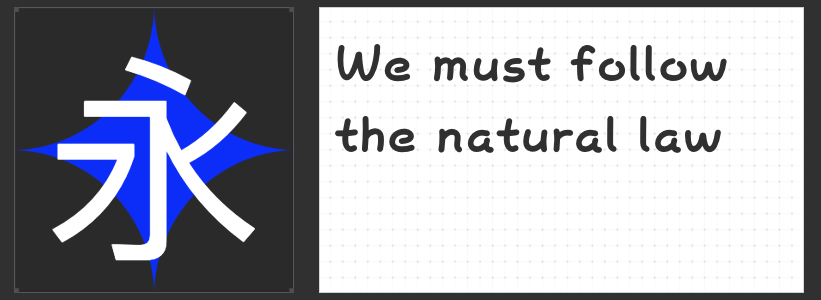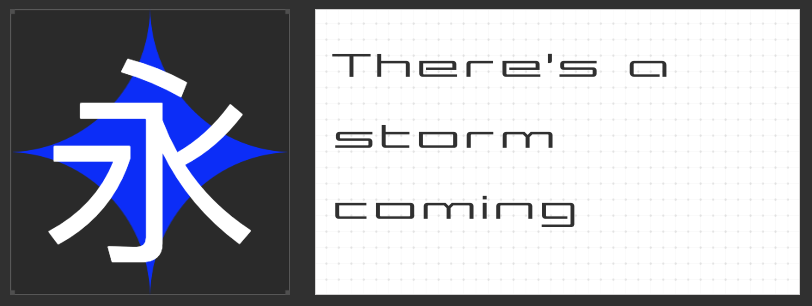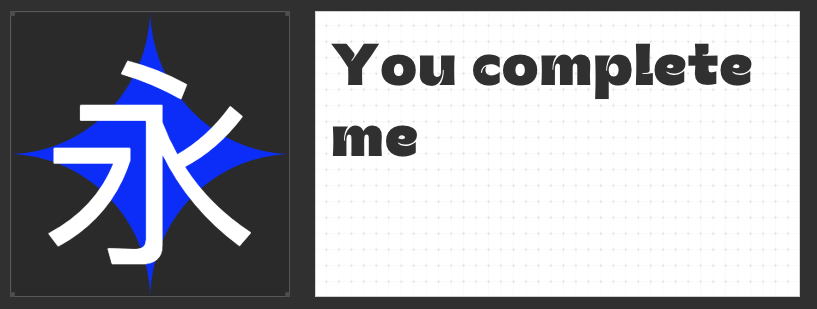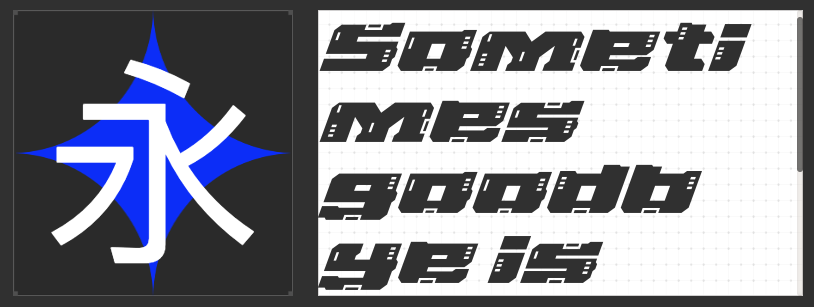
英文字体精选:四种不同风格的魅力
在字体设计的浩瀚星空中,“高手兵克”系列以其独特的创意与多变的风格脱颖而出,成为设计师们不可多得的宝藏。今天,就让我们一起走进这个充满魅力的字体家族,探索四款风格各异的英文字体。
这款字体专为封面与海报设计而生,它巧妙融合了童趣与优雅,每一个字母都像是精心雕琢的艺术品。圆润的线条与独特的造型,不仅赋予了文字以生命力,更能在第一时间吸引观众的眼球。无论是书籍封面还是电影海报,它都能以其独特的韵味成为设计中的点睛之笔。
当谈到绘本与插图设计时,怎能不提“高手兵克Natural”?这款字体以其可爱的风格著称,仿佛每一笔一划都散发着温暖的气息。它适合用于营造温馨、和谐的画面氛围,让孩子们在阅读的同时感受到字体的魅力。无论是角色对话还是旁白文字,它都能以恰当的方式融入其中,成为故事的一部分。
对于科普类设计而言,一款具有未来感和机械感的字体无疑能增添不少科技感。而“高手兵克Mechs Regular”正是这样的存在。它每一个字母的设计都透露着冷峻与力量。在介绍高科技产品或探索宇宙奥秘的科普内容中,它将成为连接现实与未来的桥梁。
最后要介绍的是“高手兵克Electronic”,一款带有复古感的字体,适用于标题与正文的设计。它仿佛穿越时空而来,将我们带回那个电子科技刚刚兴起的年代。独特的字形与粗犷的笔触,让每一个文字都充满了力量与个性。在需要营造复古氛围或强调文字重要性的场景中,它将成为你不可或缺的设计利器。
总之,各种多样化的风格与卓越的设计品质的字体越来越多,为设计师们提供了丰富的选择空间。无论你的设计需求如何,总能在其中找到那款最适合的字体。让我们一起探索更多可能,用字体为设计增添无限魅力吧!